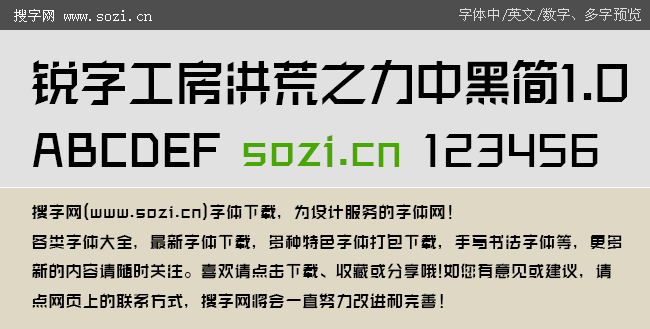
銳字工房洪荒之力中黑簡(jiǎn)
搜字網(wǎng)提供一款非常藝術(shù)的黑體銳字工房洪荒之力中黑簡(jiǎn)下載,銳字工房洪荒之力中黑簡(jiǎn)是一款字形方正的銳字工房字體,該字體極具藝術(shù)感,簡(jiǎn)潔大方,適用于包裝印刷、廣告設(shè)計(jì)、平面設(shè)計(jì)、書籍報(bào)紙等領(lǐng)域。